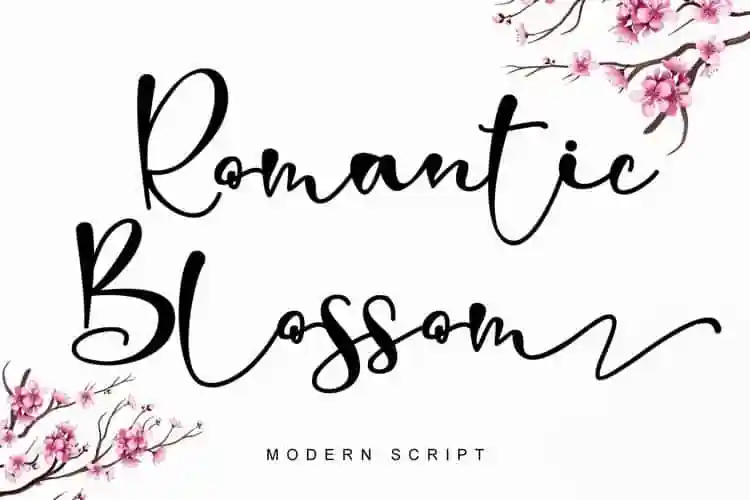
Romantic Blossom Script Font – Download Grátis
A Romántica Fonte Script é uma criação sofisticada do designer Stefani Letter que apresenta uma ligatura linda e alternativas para oferecer um visual clássico, belo e moderno. Esta fonte gráfica é ideal para aplicações como logotipos, marcas de identidade, cartas de convite, artefatos de estação, designs para casamentos e postagens no Instagram, entre outras utilizações. Suas características exóticas tornam-a uma opção perfeita para quem busca um toque único em seu projeto gráfico. Com sua aparência elegante, a Romántica Fonte Script é adequada para criar ambientes sofisticados que expressam elegância e requinte sem comprometer a modernidade. Seja você um designer de arte ou criador de conteúdo digital, adotar esta fonte pode ajudá-lo a destacar-se entre a multidão. Seu uso em cartões de convite românticos para casamentos, em logomarcas que expressam seu nome ou em design de postagens de rede social com uma paleta de cores e formas distintivas – a Romántica Fonte Script tem tudo o que você precisa para tornar suas ideias ainda mais inspiradoras.